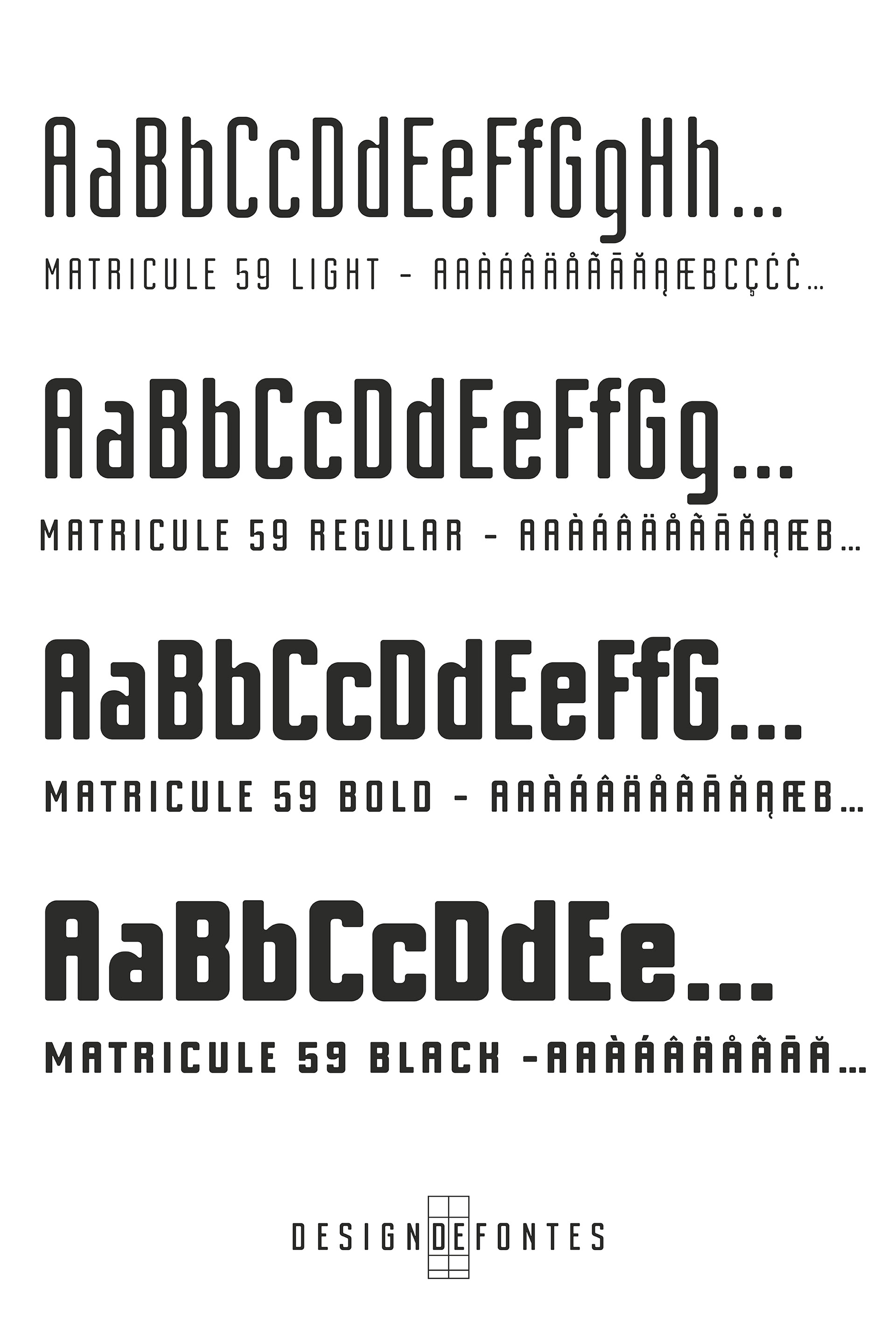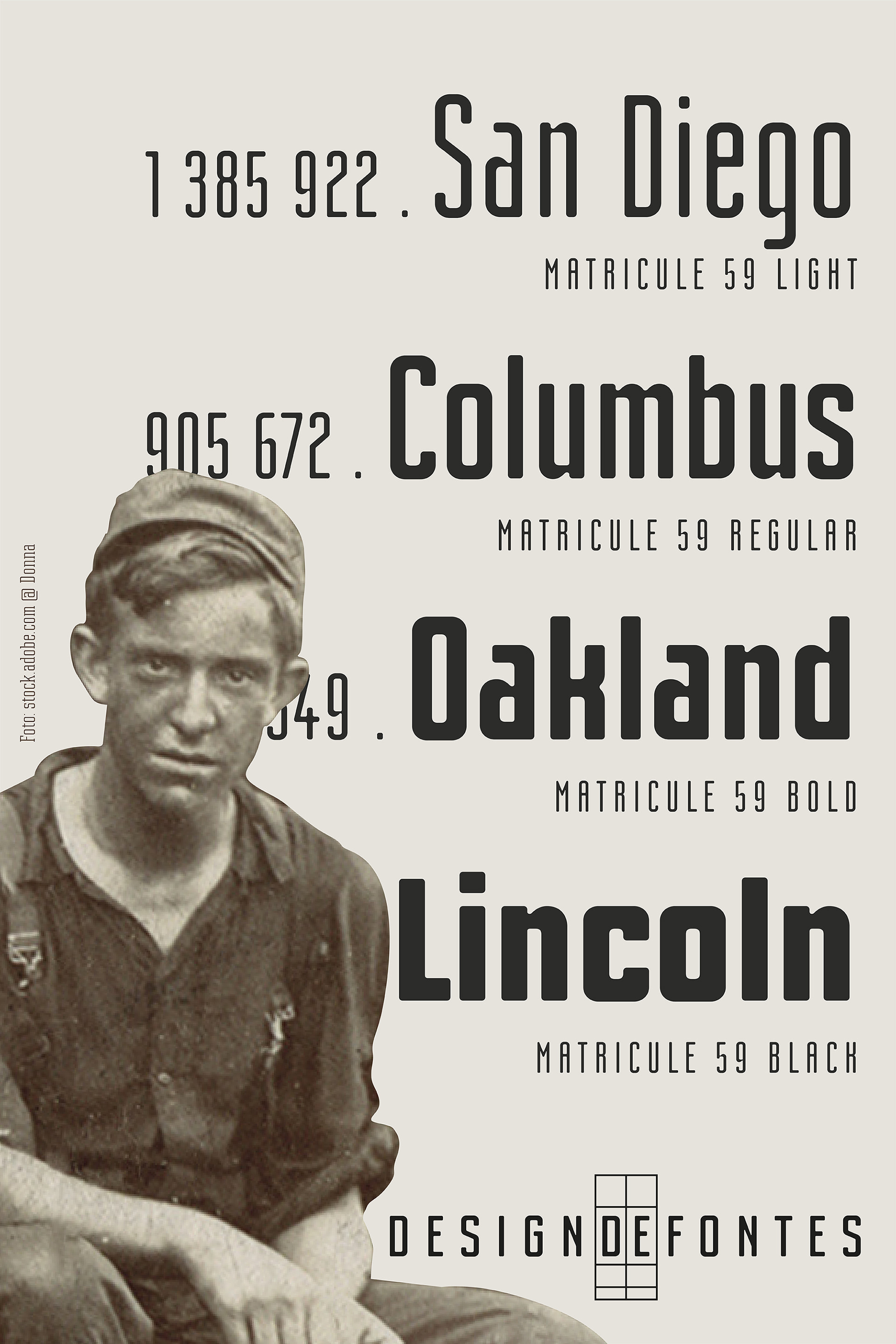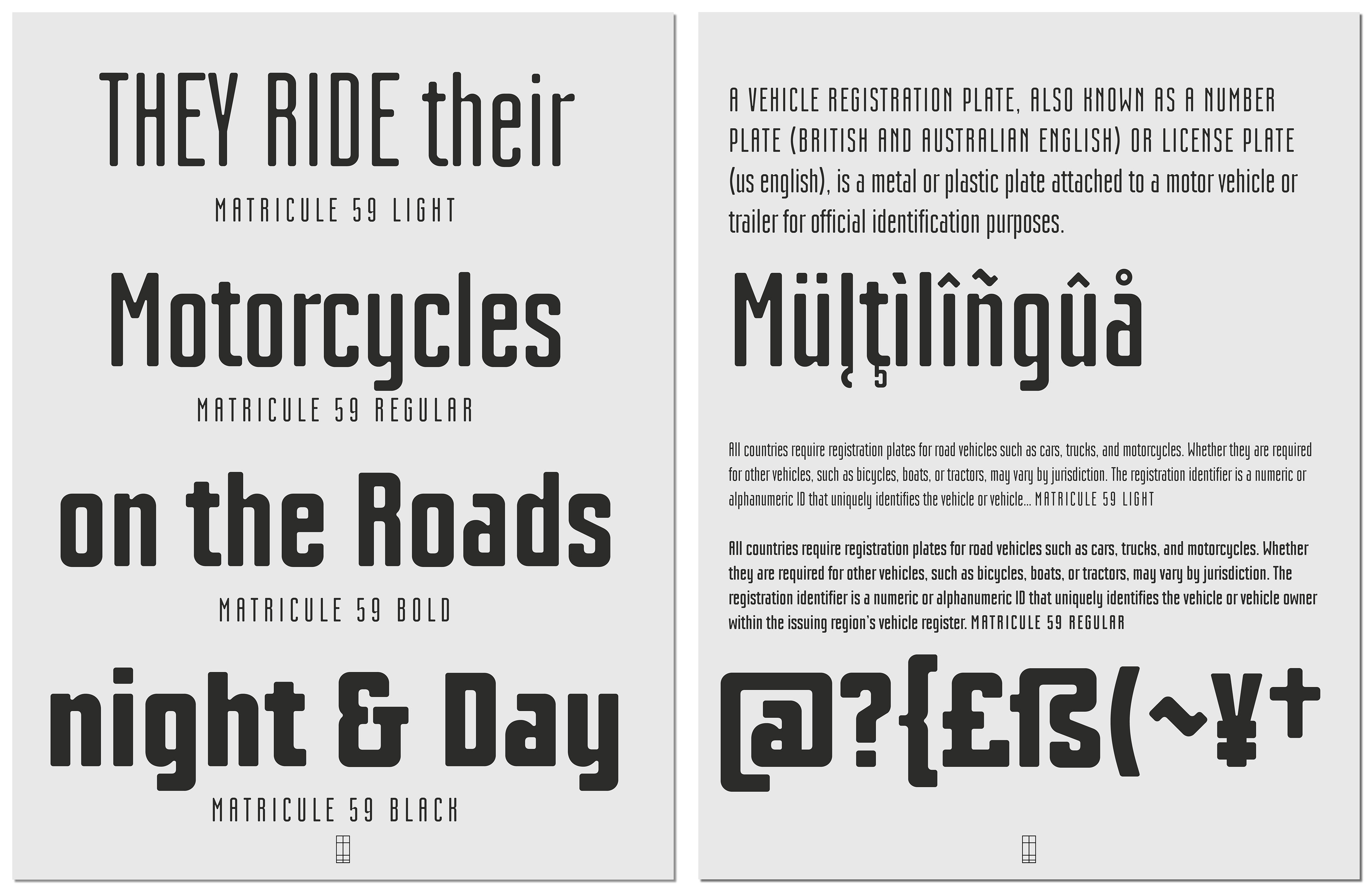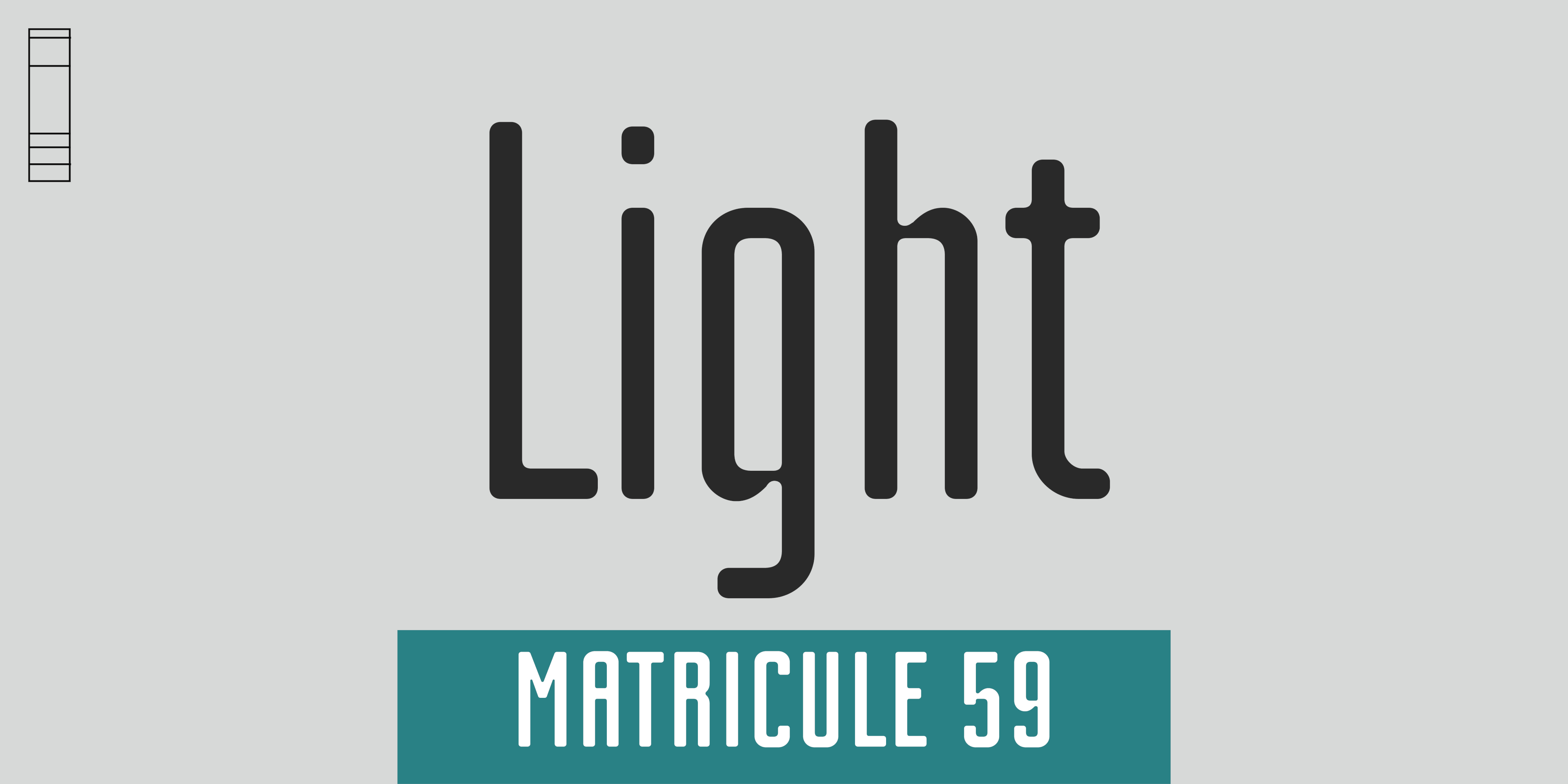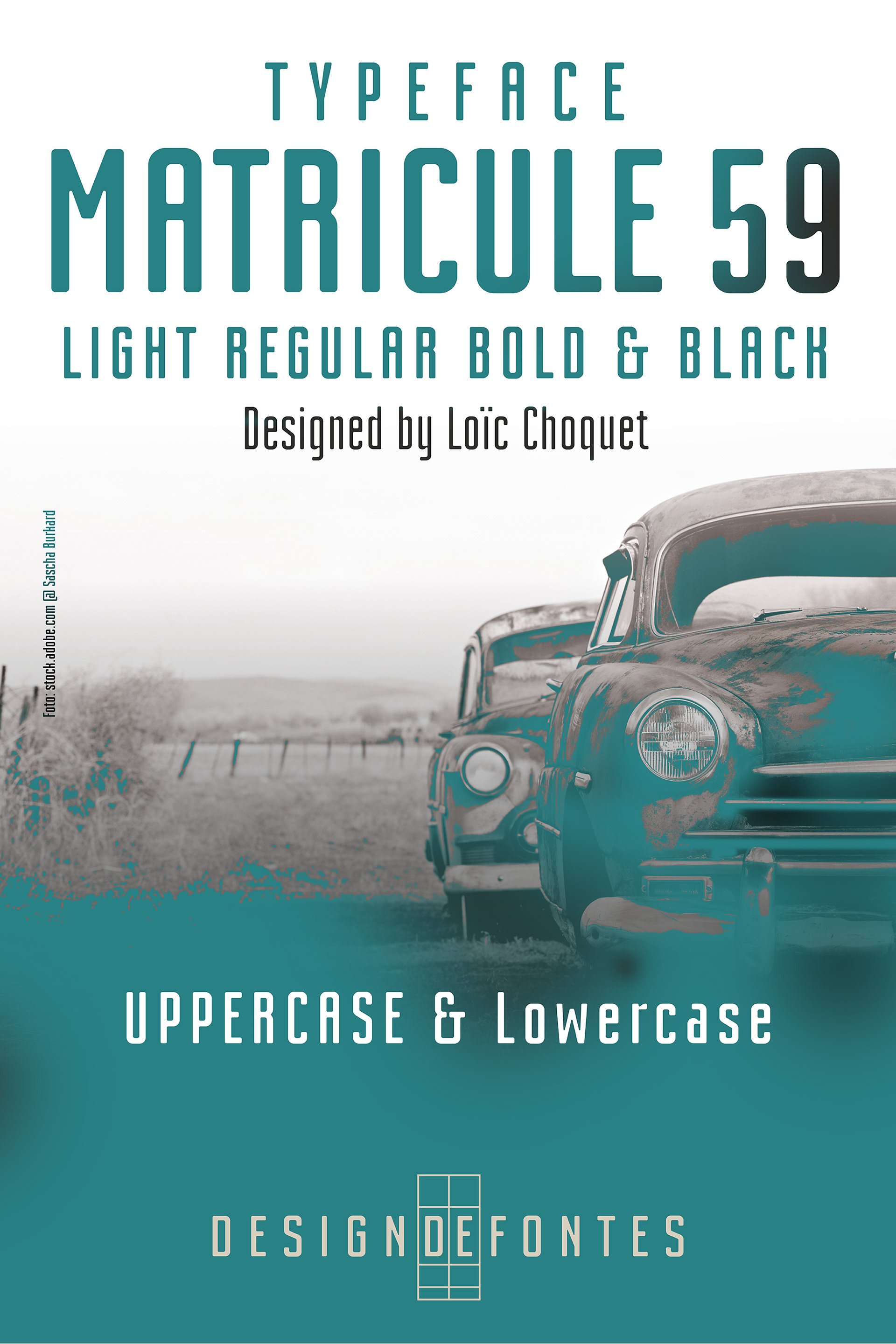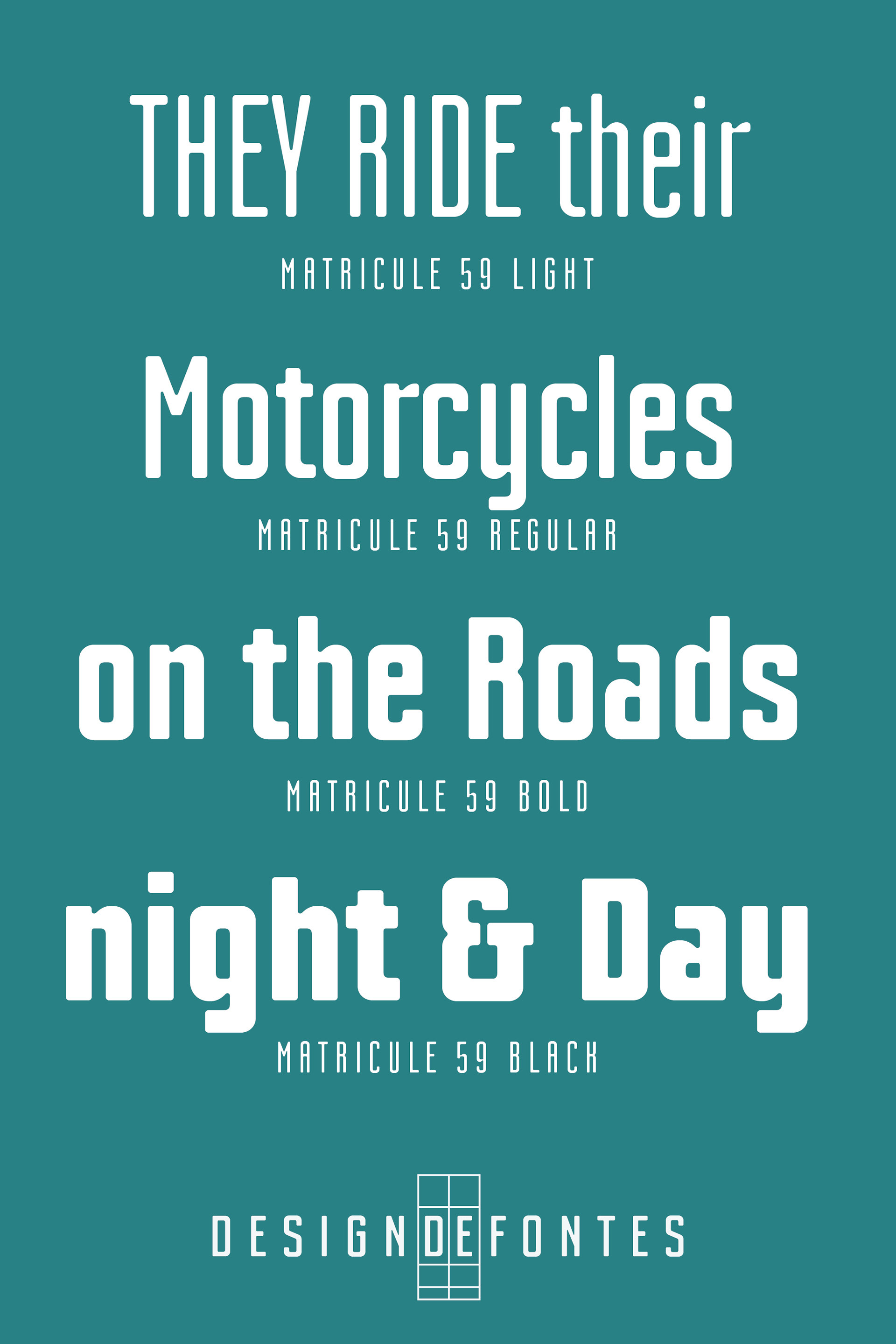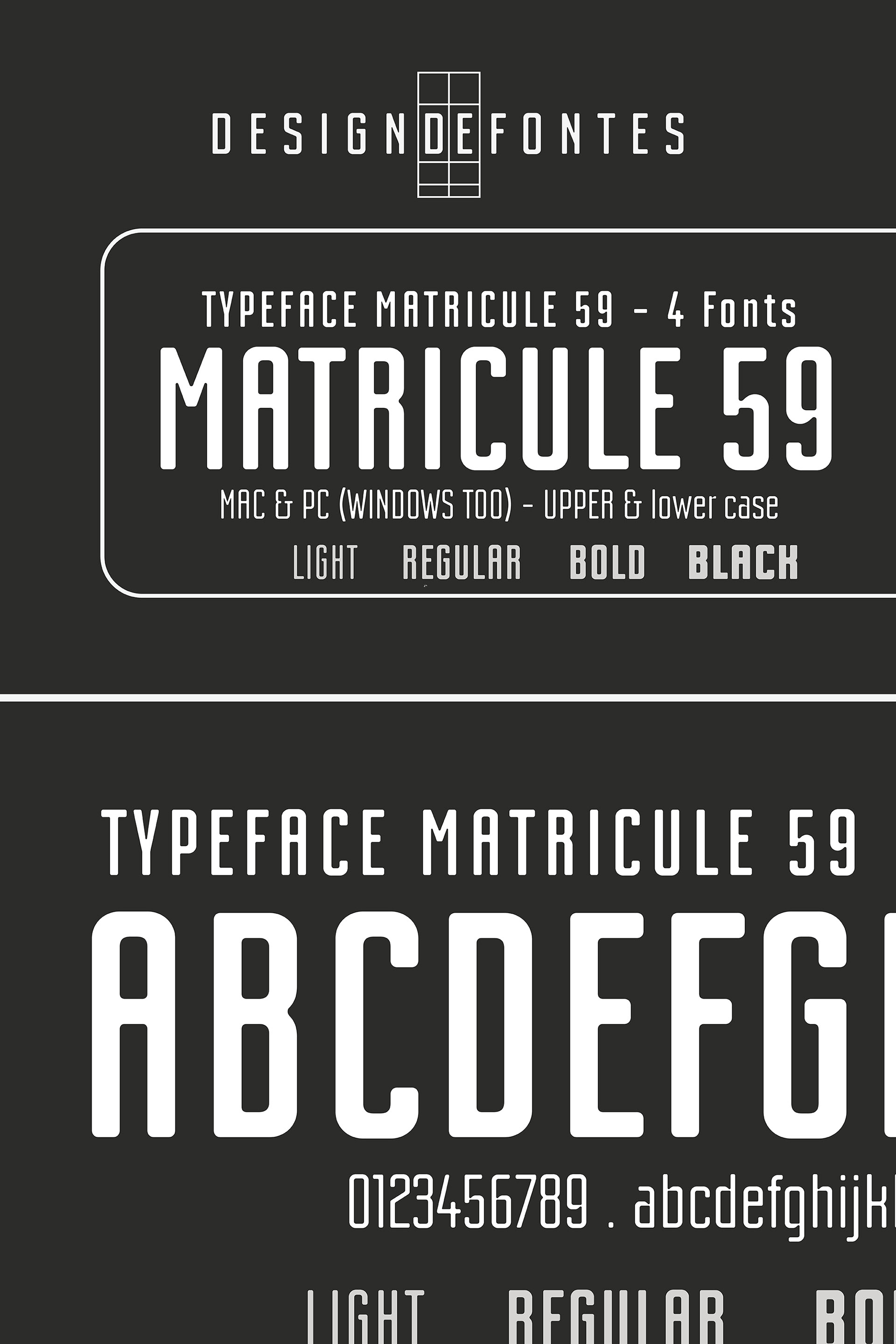
CARACTèRE TYPOGRAPHIQUE MATRICULE 59
SCHRIFT MATRICULE 59
(Loïc Choquet > designdefontes)
Matricule 59 est un caractère typographique existant sous la forme de 4 fontes. Ces fontes sont utilisables pour des projets éditoriaux, des logotypes, affiches, packaging, etc. Chaque fonte comprend 359 glyphes répondant aux besoins de composition de textes en alphabet latin.
Die Matricule 59 Schriftfamilie besteht aus 4 Schriften. Sie eignet sich hervorragend für Editorial-Projekte, Logotypen, Plakate, Verpackungen und mehr. Die Schrift enthält 359 Glyphen und bietet eine hohe Flexibilität für die Unterstützung lateinischer Sprachen, um sämtlichen typografischen Anforderungen gerecht zu werden.
Matricule 59 est un caractère dont le design et inspiré par les plaques d’immatriculations et plus particulièrement par les déformations provoquées par la pression des caractères dans les plaques métalliques. Ces déformations donnent aux caractères un style spécifique notamment concernant les déliés de liaisons de ces caractères. Matricule 59 est la version ultra condensée de Matricule, un caractère dessiné par Loïc Choquet.
Matricule 59 ist eine Schrift, deren Design von Nummernschildern inspiriert ist, insbesondere von den Verformungen, die durch den Druck der Buchstaben auf die Metallplatten entstehen. Diese Verformungen verleihen den Zeichen einen spezifischen Stil, insbesondere in Bezug auf die feinen Verbindungen der Buchstaben. Matricule 59 ist die ultra-kondensierte Version von Matricule, einer Schrift, die von Loïc Choquet entworfen wurde.
Matricule 57 est prête à l’emploi pour 89 langues différentes
Matricule 57 kann in 89 unterschiedlichen Sprachen genutzt werden
4 STYLES (4 fontes) : Light, Regular, Bold and Black. Chaque fonte contient 359 glyphes permettant ainsi l’emploi de ce caractère dans au moins 89 langues différentes.
4 STILE (4 SCHRIFTEN): Light, Regular, Bold und Black.
Jede Schrift enthält 359 Glyphen und unterstützt bis zu 89 verschiedene Sprachen.